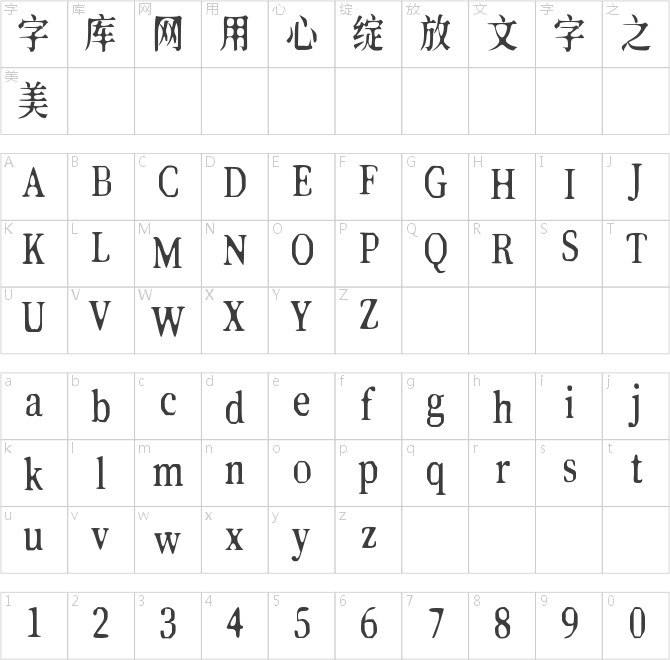
字體名稱: 新愚公的滄桑
新愚公的滄桑
思源宋體進行改造的一款字體。這款字體加入了隨機的扭曲效果,讓這款字體蒙上了一種歲月的斑駁滄桑感。這款扭扭曲曲的字體,也適合用于類似古印字體的設計,也是挺有特色的。
新愚公的滄桑字體字庫是一款讓人賞心悅目、百看不厭的中文字體,適合各類廣告和產品包裝設計應用,字體大小12.2MB,格式為ttf字體,上傳用戶是云泥,作者/版權方為新愚公